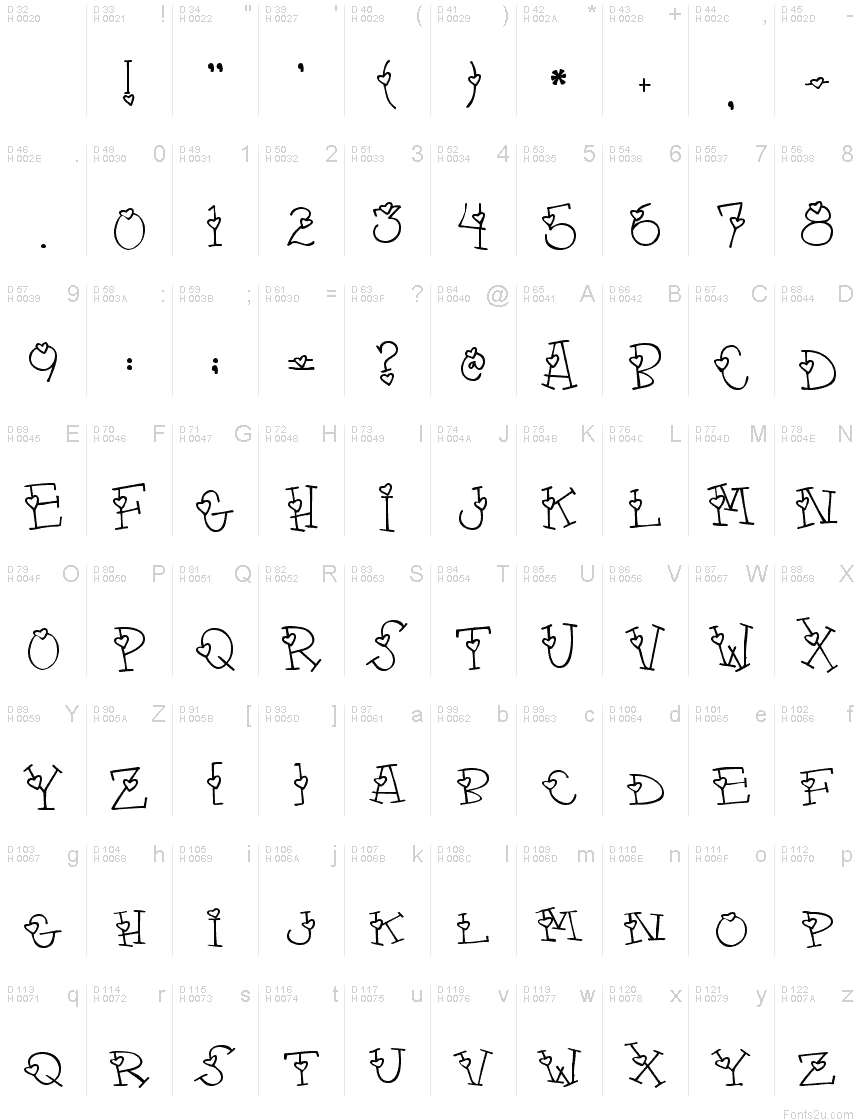
4 My Lover di Jakob Fischer (Pizzadude) è un font gratuito per San Valentino, caratterizzato da un fascino informale e disegnato a mano. Ogni lettera si inclina e ondeggia con tratti sottili e minuscoli cuoricini, proprio come uno scarabocchio sul margine di una lettera d'amore. Il tratto risulta leggermente graffiante e imperfetto al punto giusto, donando ai tuoi layout un'energia spontanea e romantica che i font script troppo perfetti non possono offrire.
Con 4 My Lover puoi aggiungere un tocco di giocoso romanticismo a biglietti di San Valentino, inviti, post sui social, adesivi, etichette regalo e packaging per dolci o fiori. Questo font gratuito dà il meglio di sé se usato in grande formato, lasciando traspirare i dettagli a forma di cuore, e si abbina dolcemente a un semplice sans serif per il testo principale o le didascalie.